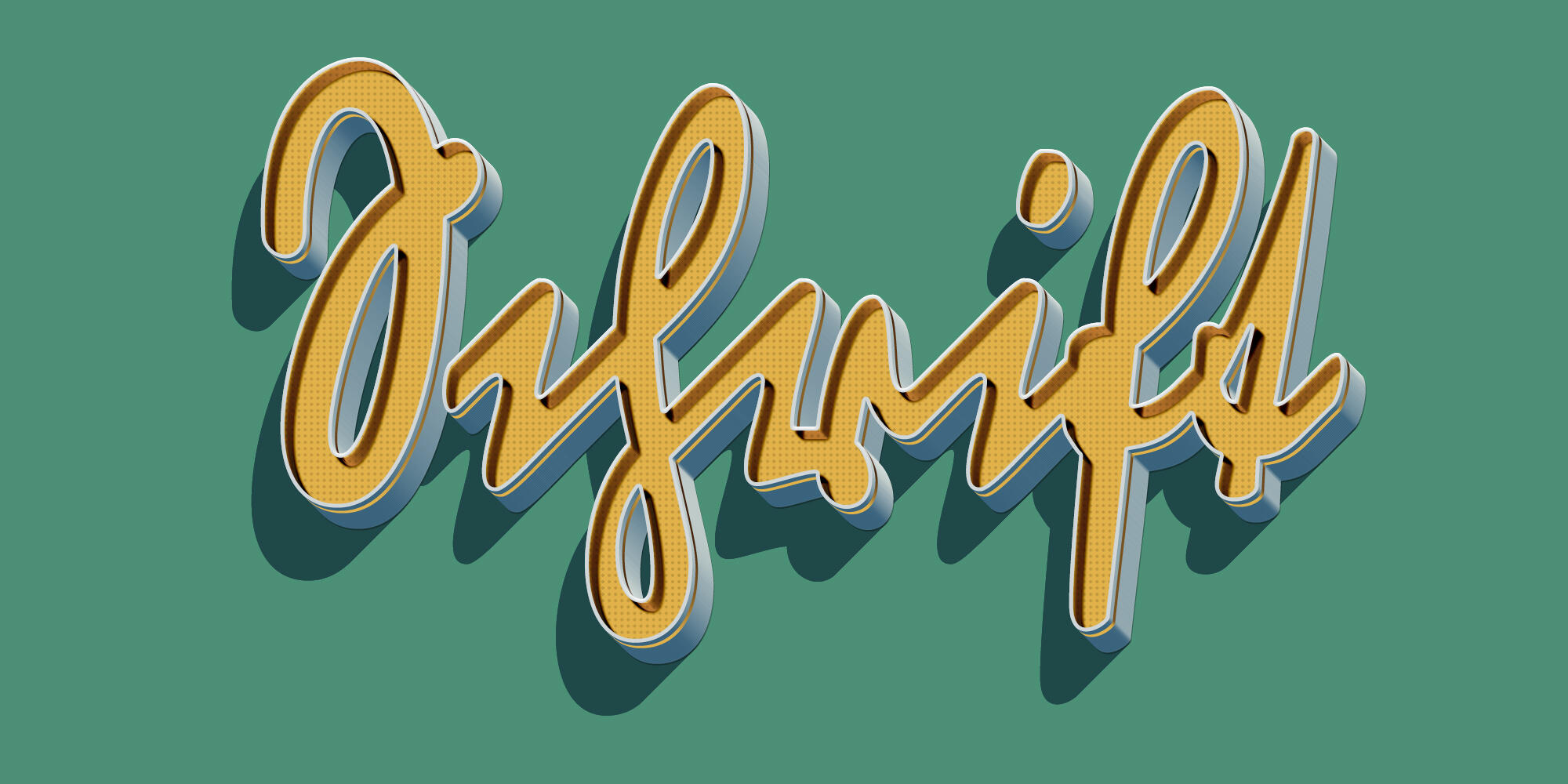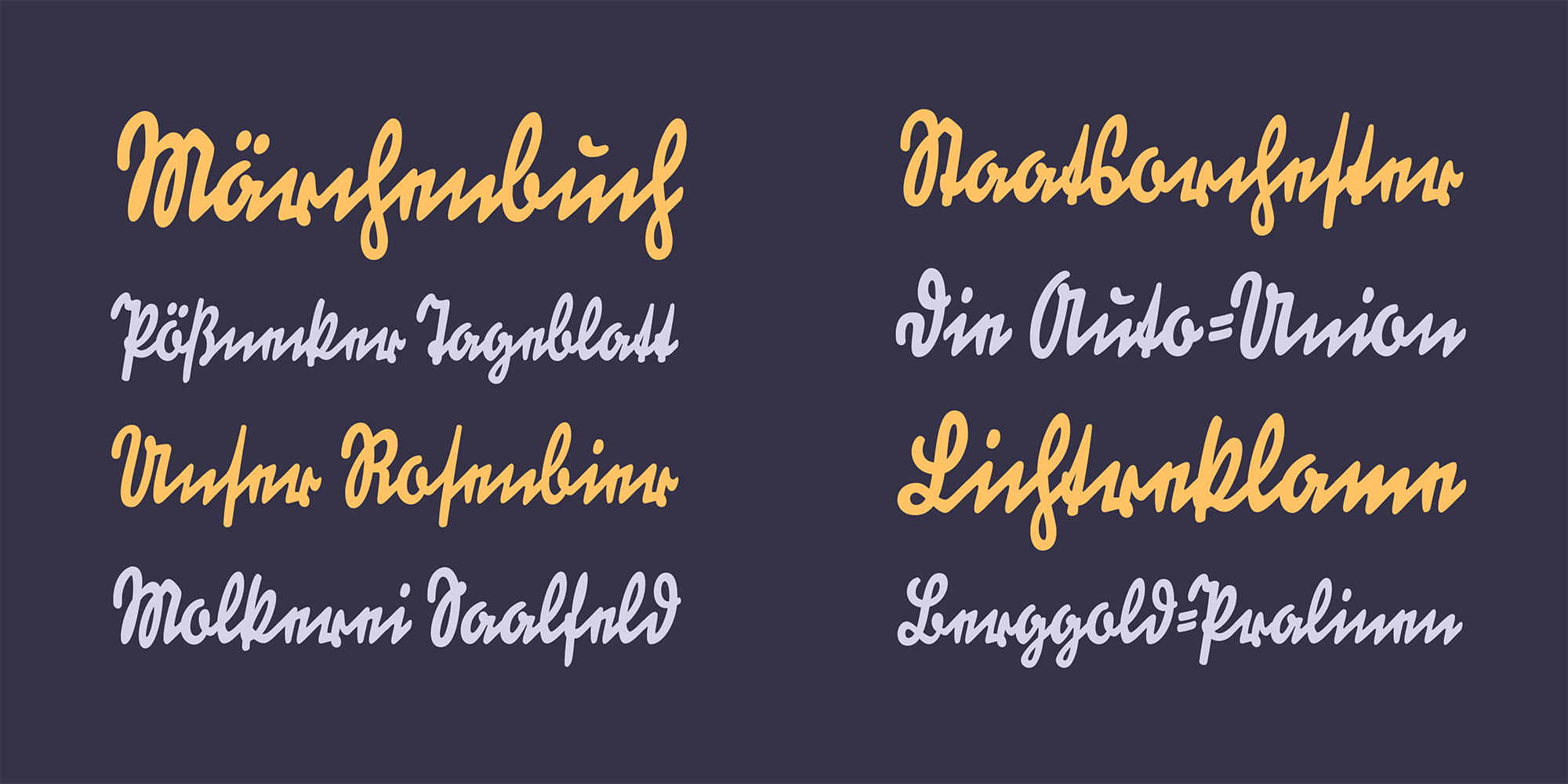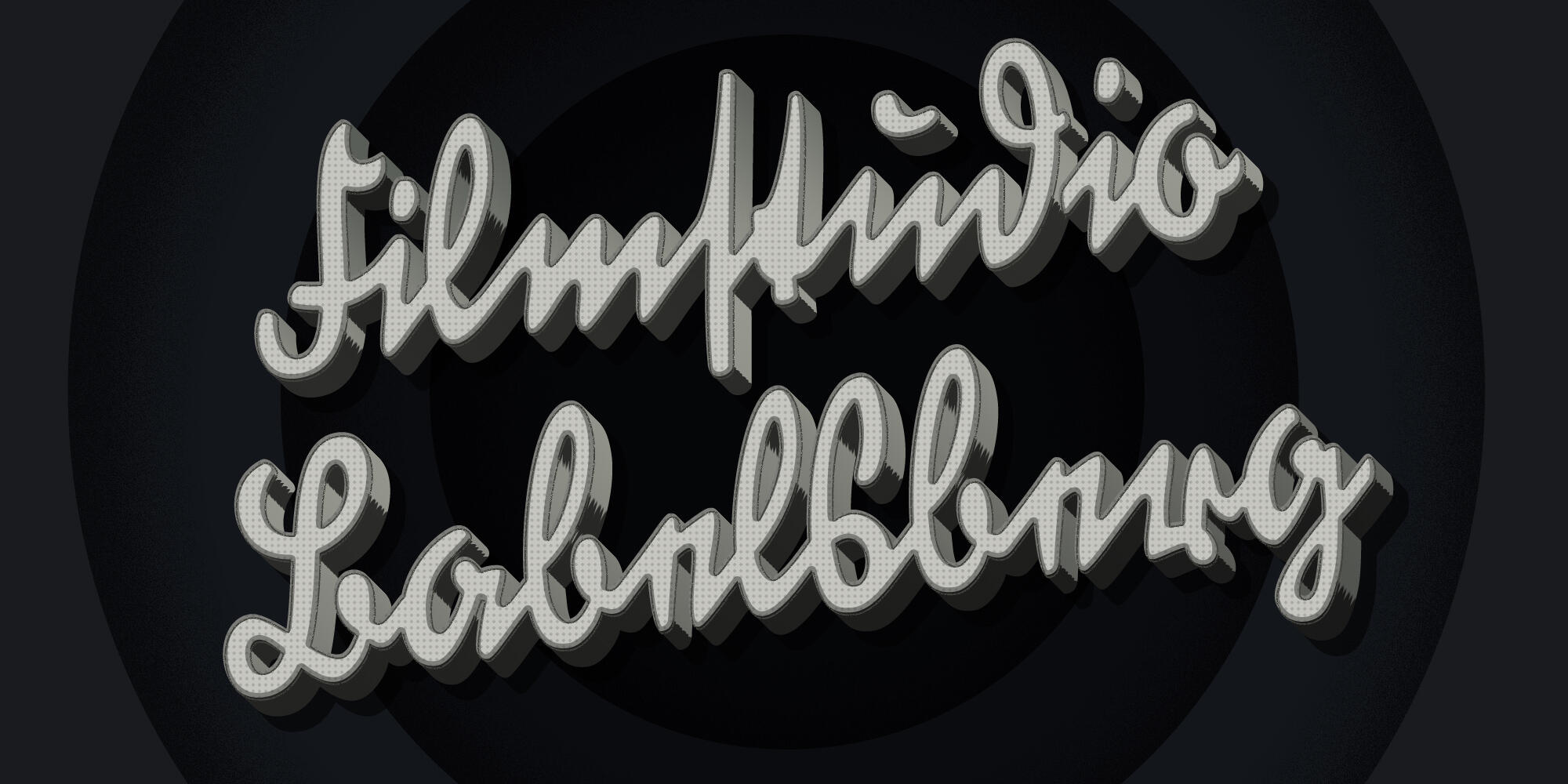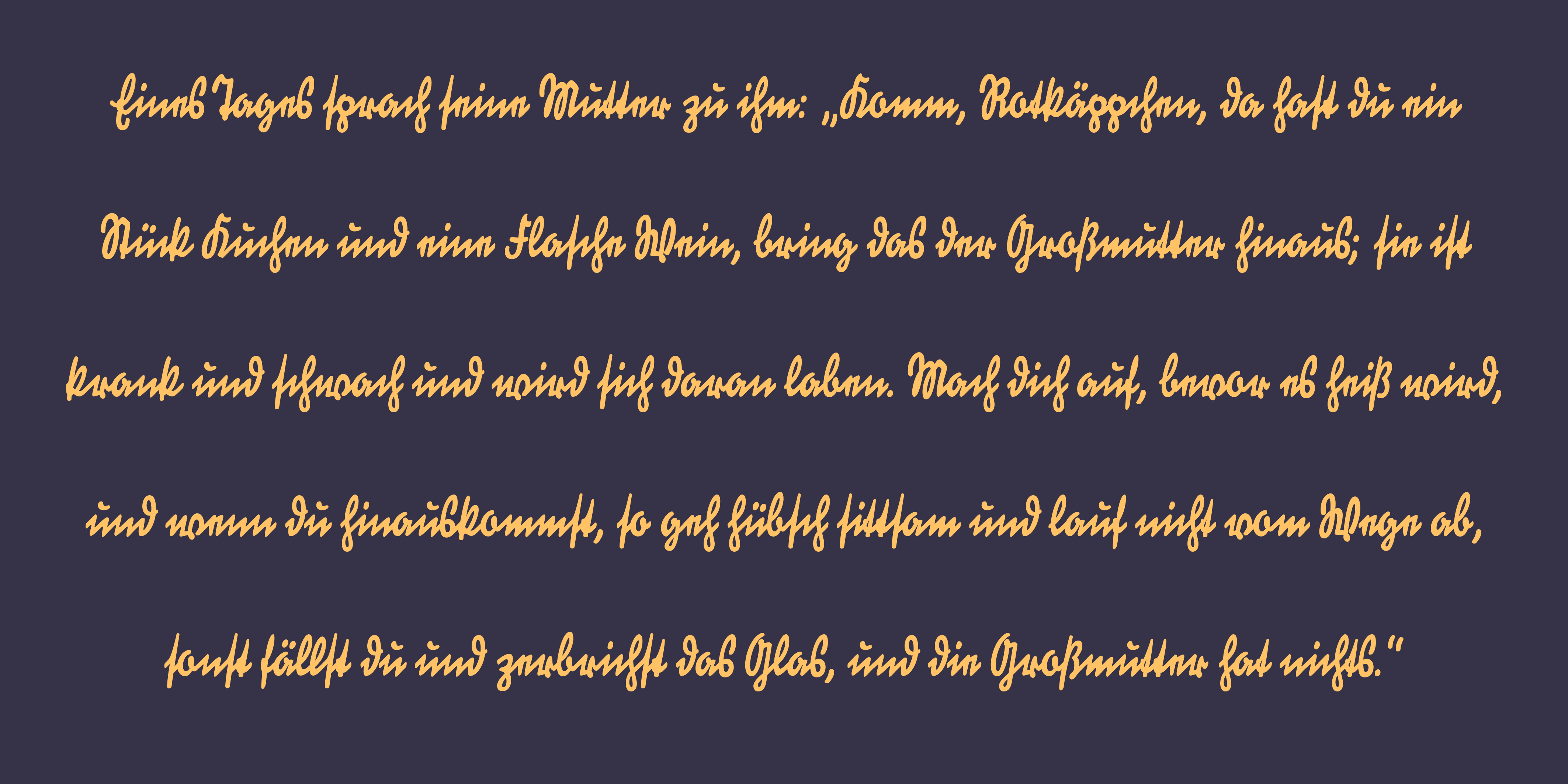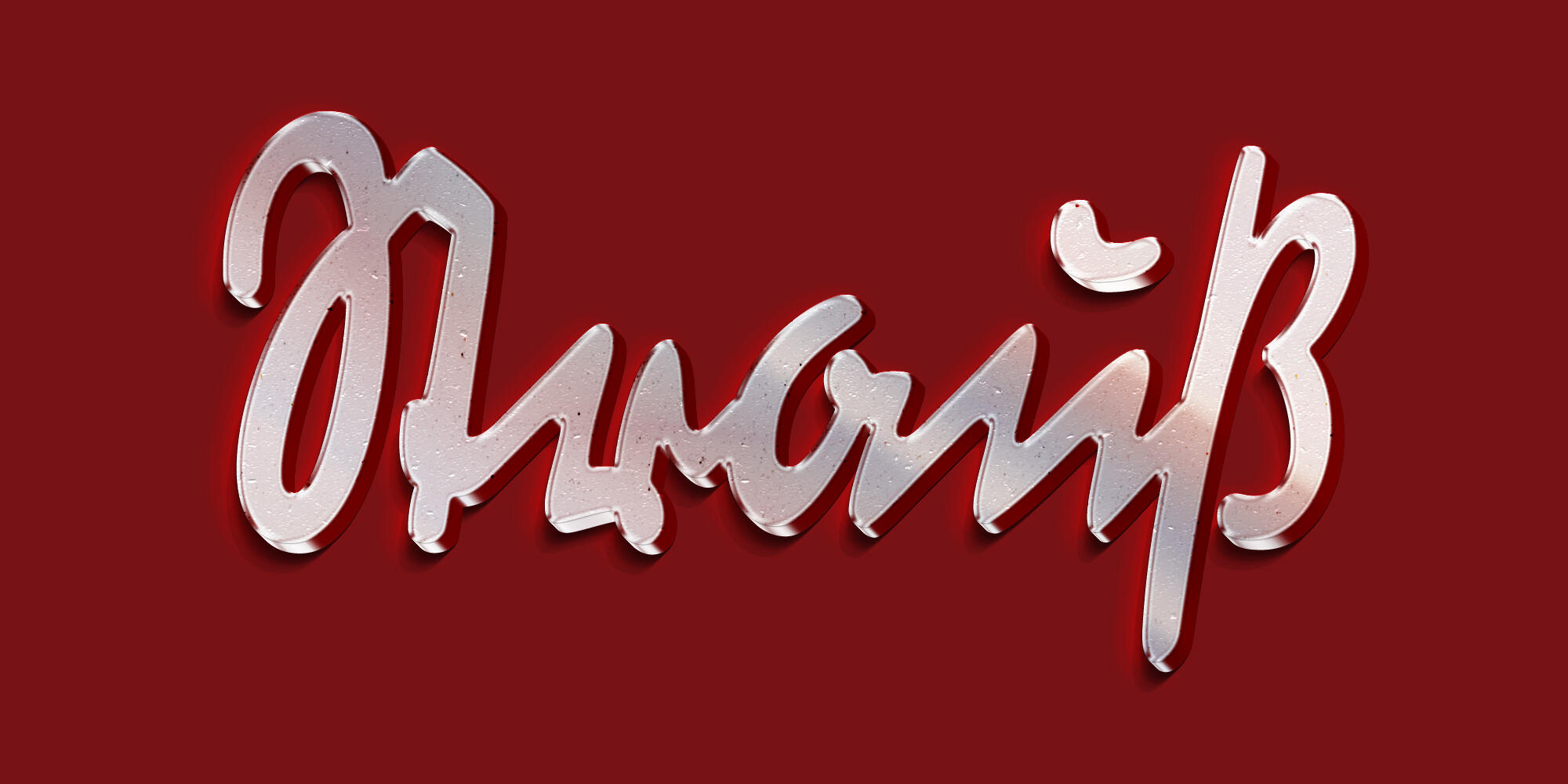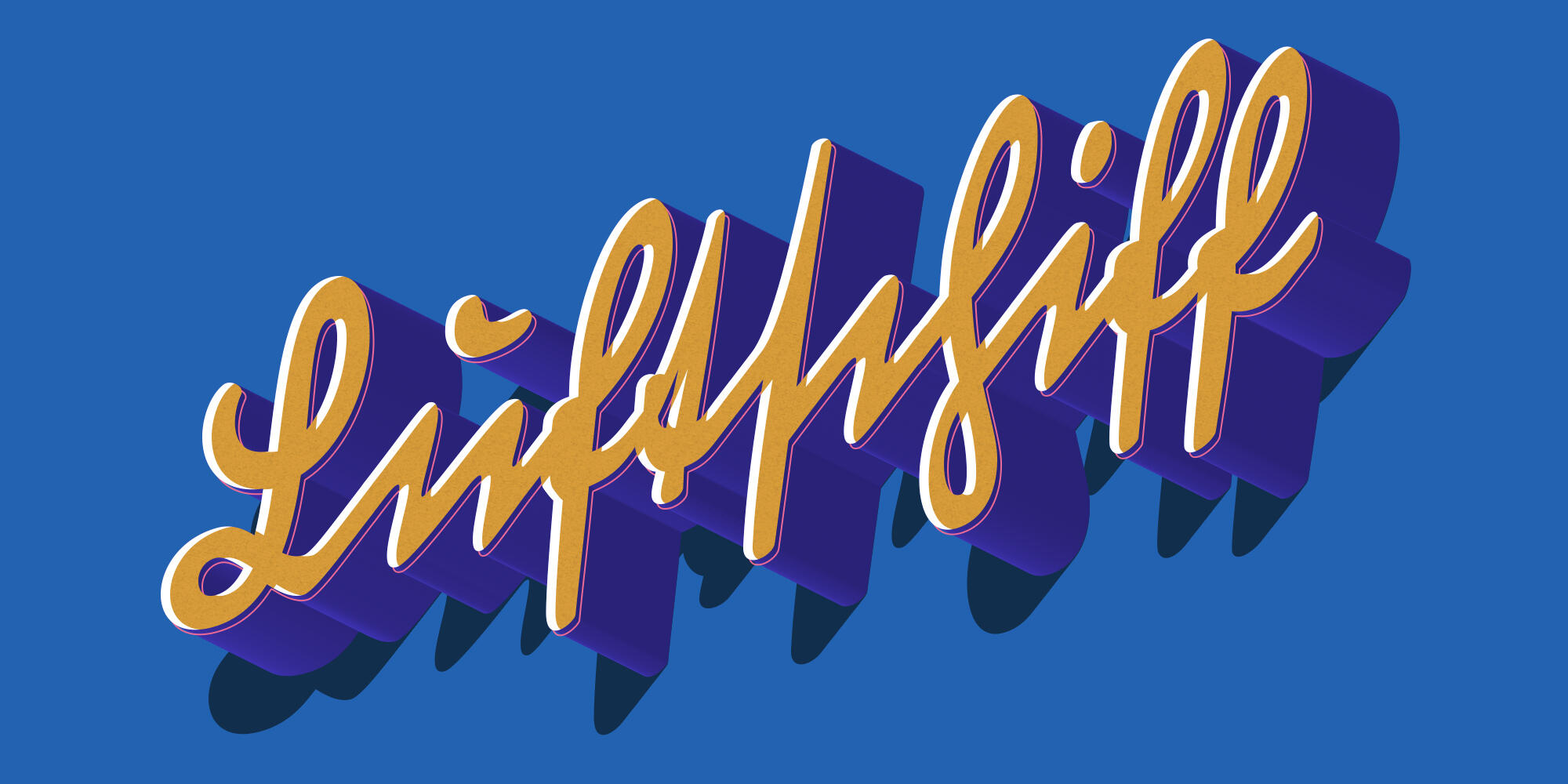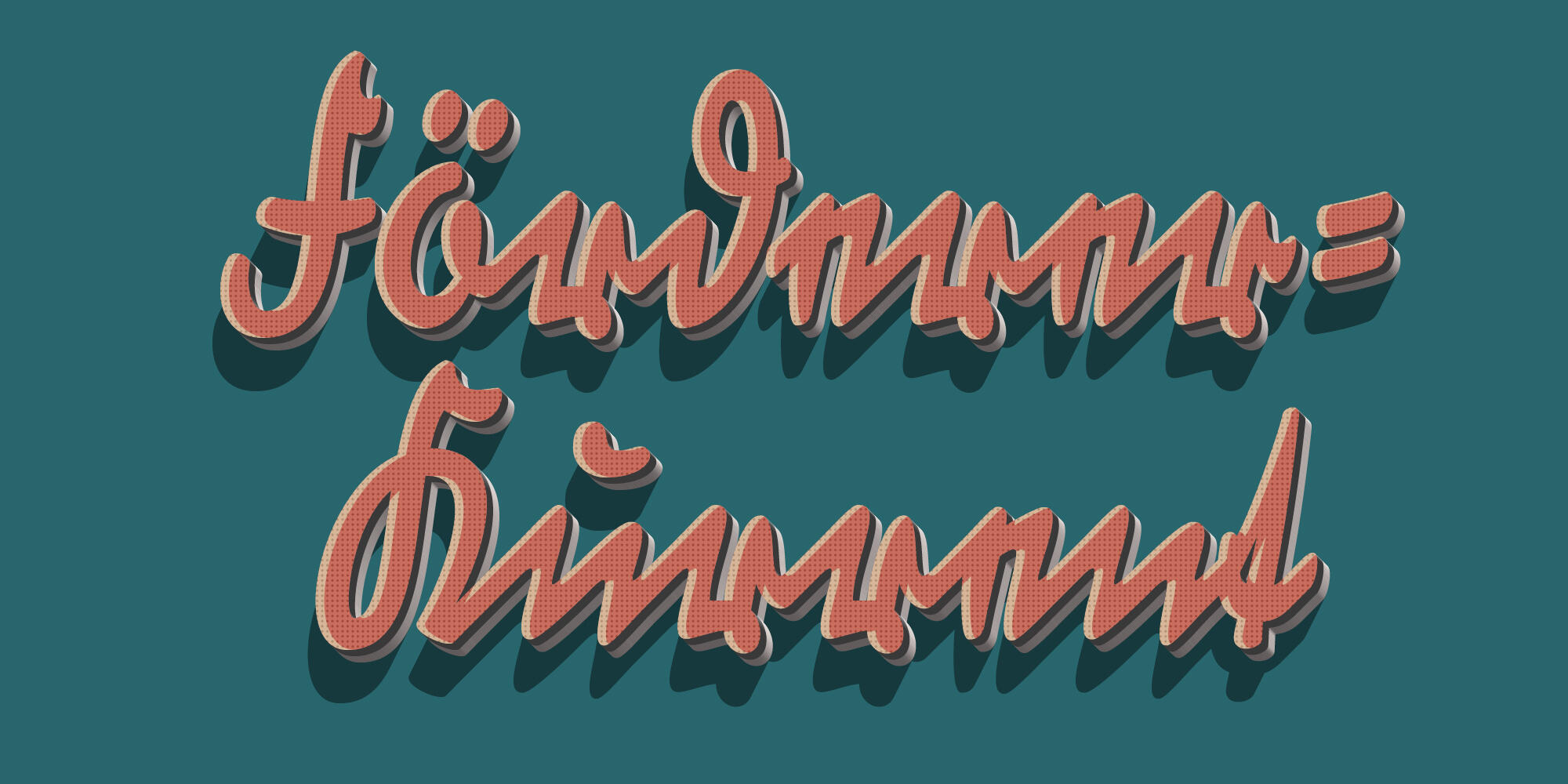
Eine vollständige Digitalisierung der Werbekurrent Deutsch-Signal basierend auf den Original-Produktionsmaterialien der H. Berthold AG. Diese Schrift komplettiert die bereits als FDI Lettograph verfügbare Digitalisierung der Signal-Familie.
Über die OpenType-Funktionen Standardligaturen (LIGA) und kontextbedingte Varianten (CALT) wird eine nahtlose Verbindung für beliebige Buchstabenpaare erreicht und Buchstabenanschlüsse für Wortanfänge und -enden werden für eine natürliche Schreibwirkung optimiert bzw. wo nötig unterdrückt. Weitere Details im enthaltenen Schriftmuster-PDF.